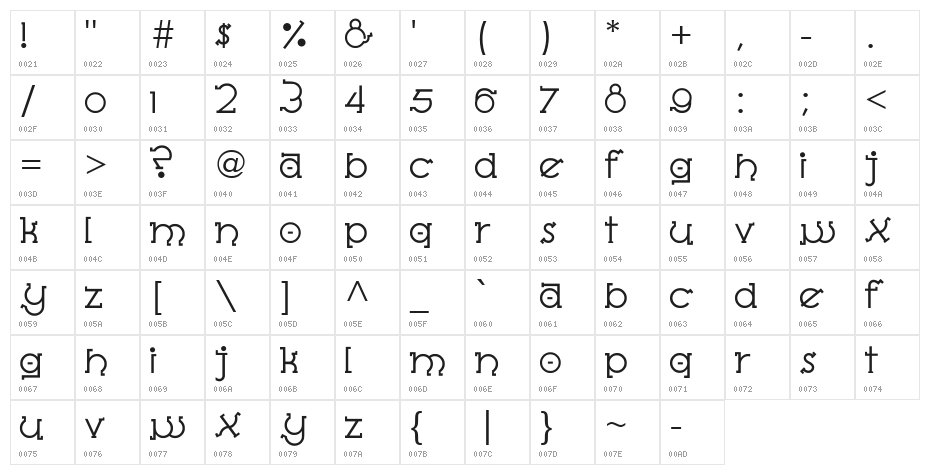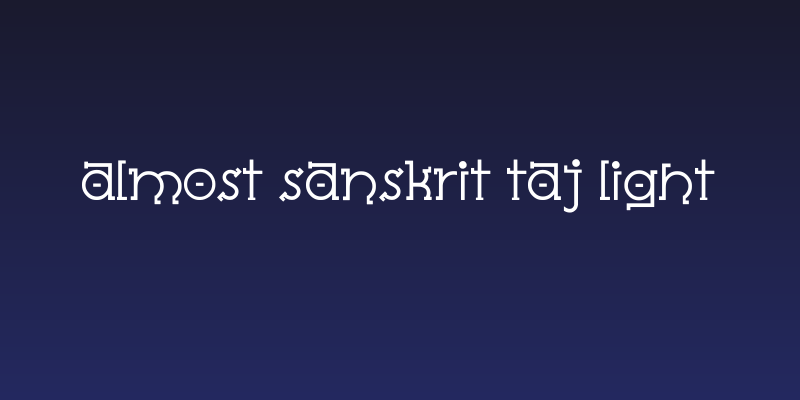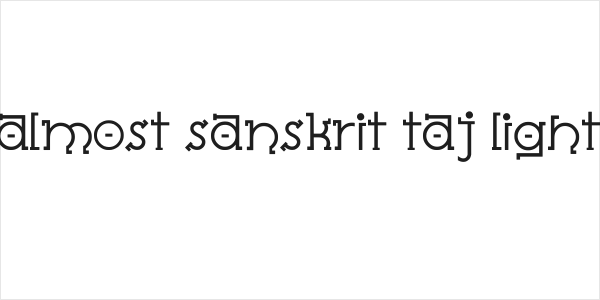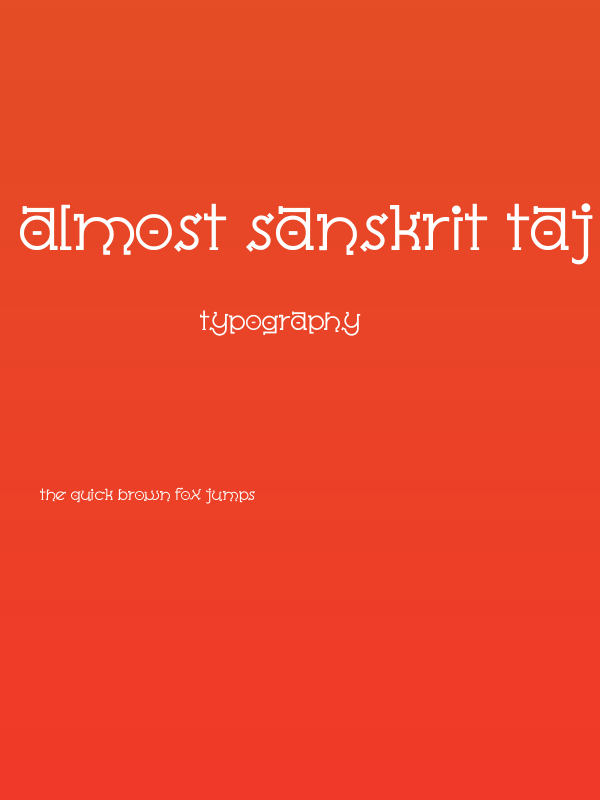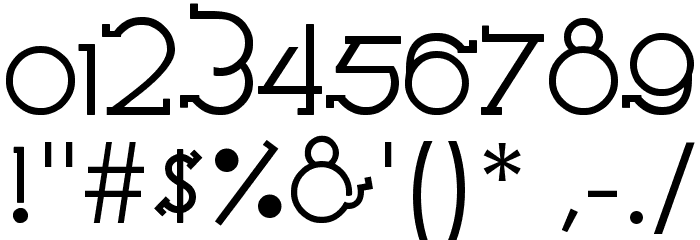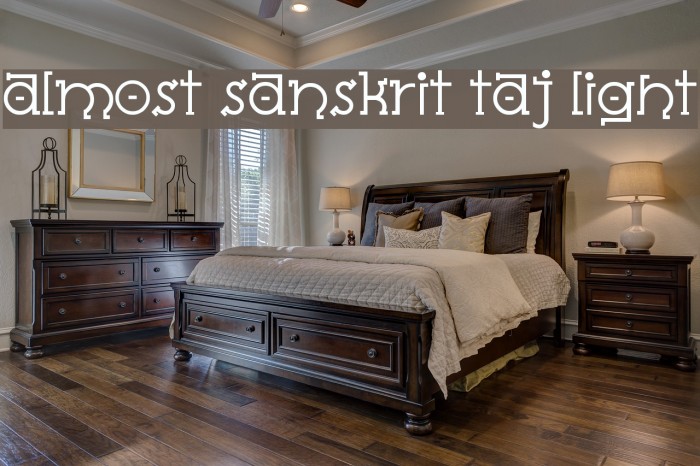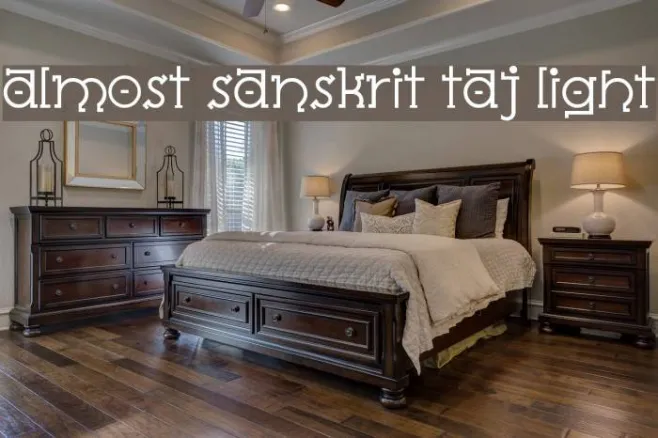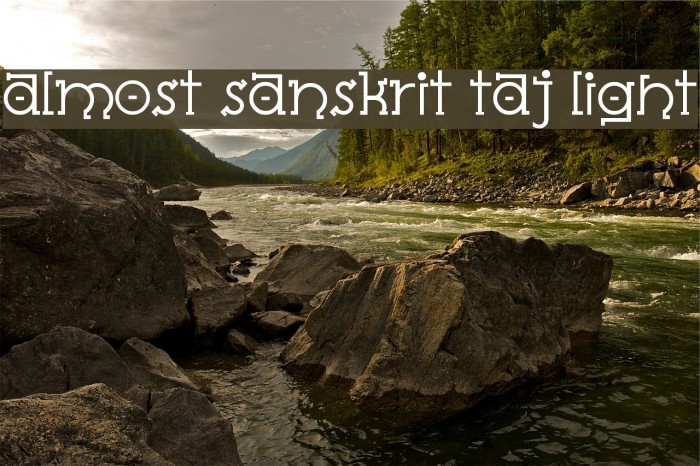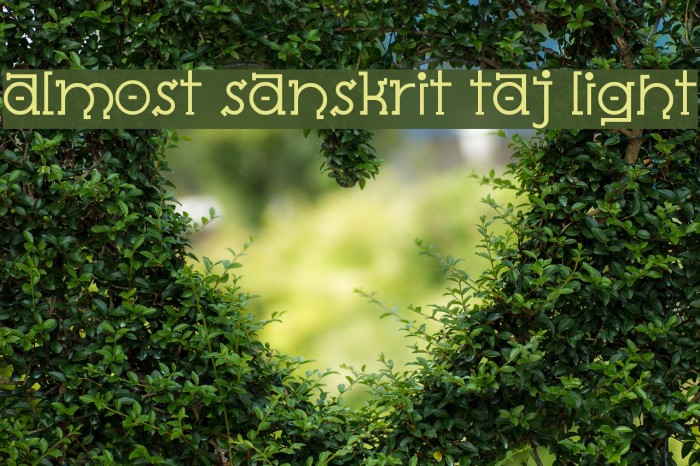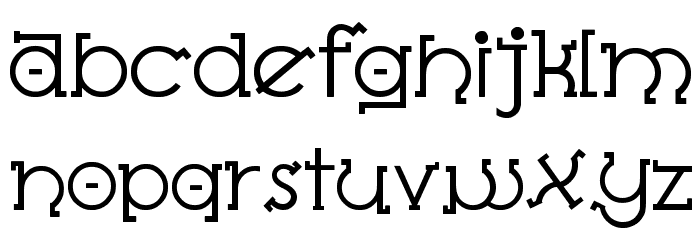
Almost Sanskrit Taj Light Font
| Caso d'uso | Logos, Posters, Artistic projects |
| Progetti proposti | Ideal for branding, logos, posters, and artistic projects that require a touch of cultural elegance and modernity. |